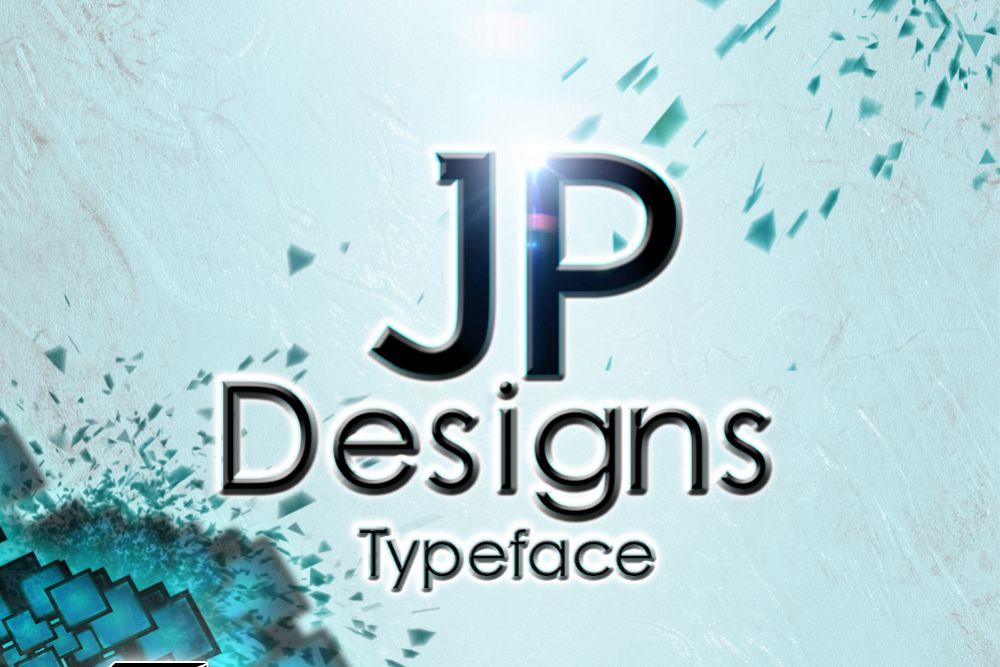
JP Designs es un estilo de fuente básico dirigido a la presentación corporativa, adaptable, fácil de leer y muy profesional al momento de realizar impresiones físicas.